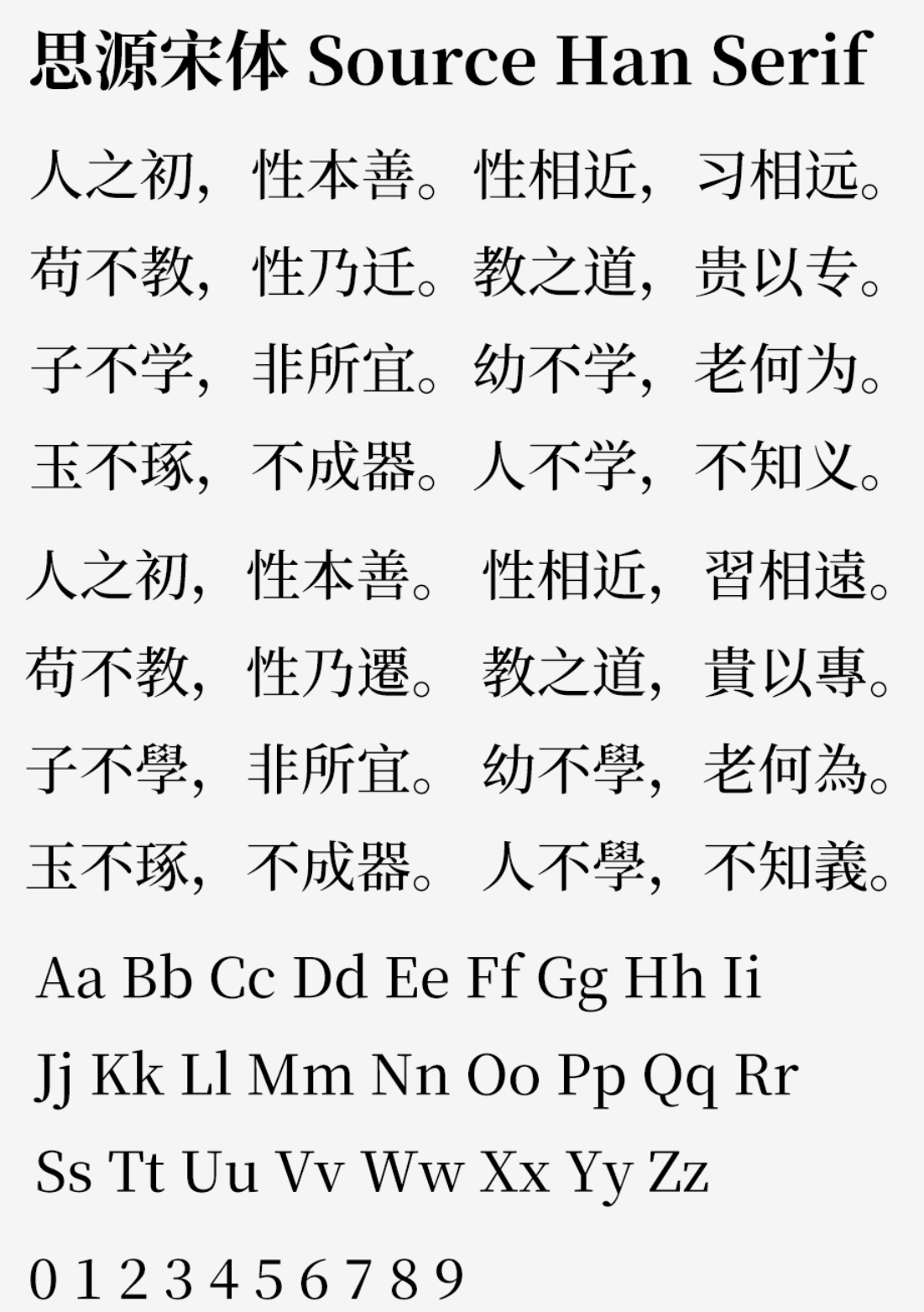
思源宋体(Source Han Serif)是 Adobe 与 Google 合作开发的最新泛 CJK 字体,它是对应于思源黑体的宋体字体。思源宋体与思源黑体这两种字体是为了响应统一设计的需求,以服务于东亚 15 亿人口。
思源宋体支持四种不同的东亚语言(简体中文、繁体中文、日语和朝鲜语),该字体还包含多个西方字形,支持拉丁语、希腊语和西里尔文脚本,这些字形均来源于 Source Serif。思源宋体总共拥有七种粗细字重,共设计了458745个汉字。也就是说每一种字重包括65535个字形。
思源宋体和思源黑体一样针对屏幕显示进行了优化,但思源宋体具有截然不同的风格,适合用于文学性较强的文本或优雅时尚的标题,打印效果也非常优美。